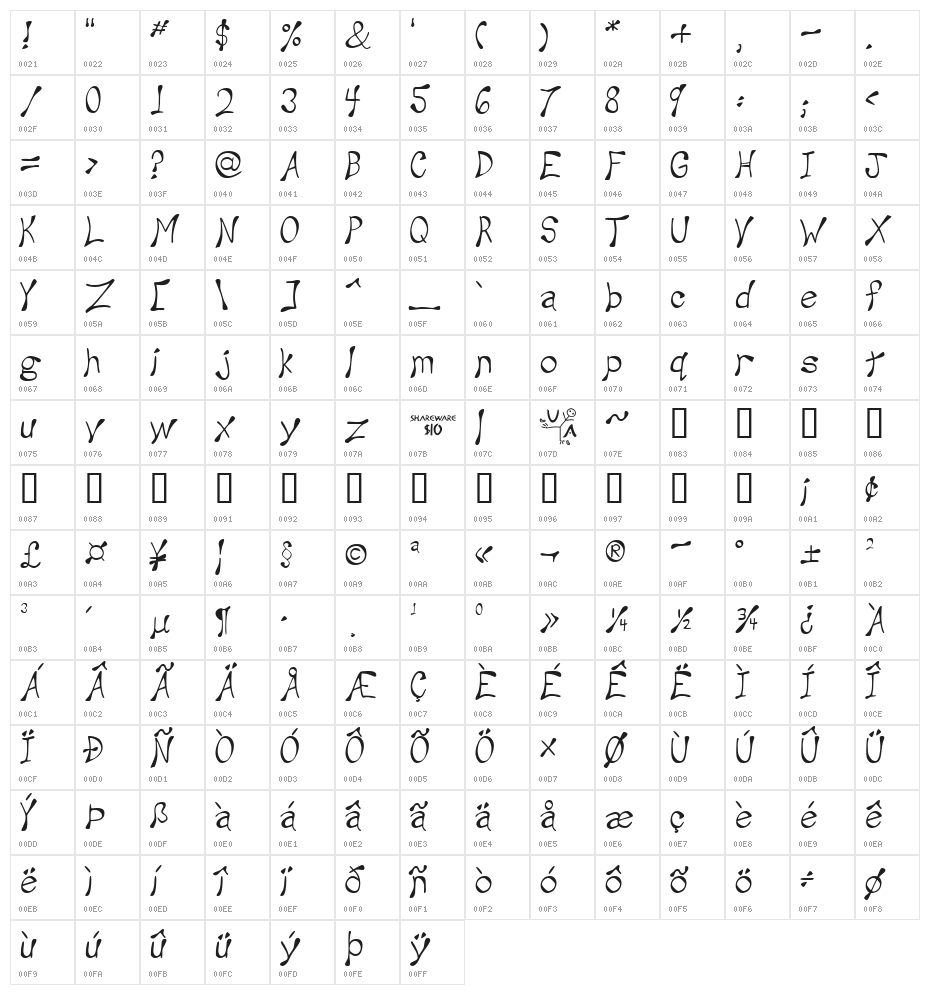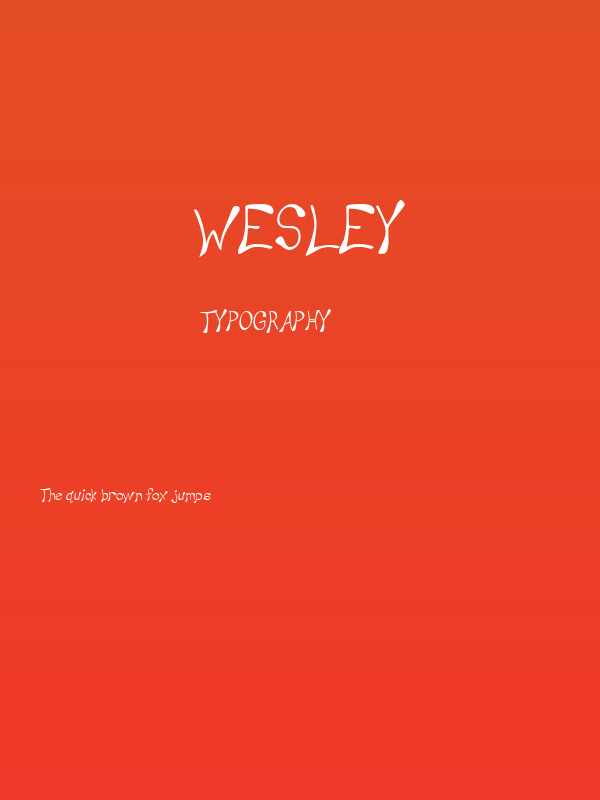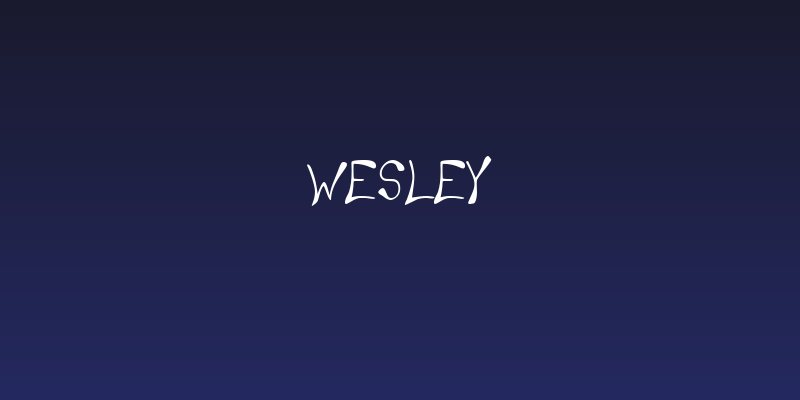
Wesley Font
| श्रेणियाँ | Kids |
| समग्र शैली | Decorative |
| उपयोग का मामला | Headlines, Logos, Posters |
| सुझाए गए प्रोजेक्ट | Ideal for children's books, creative posters, playful branding, and informal invitations. |